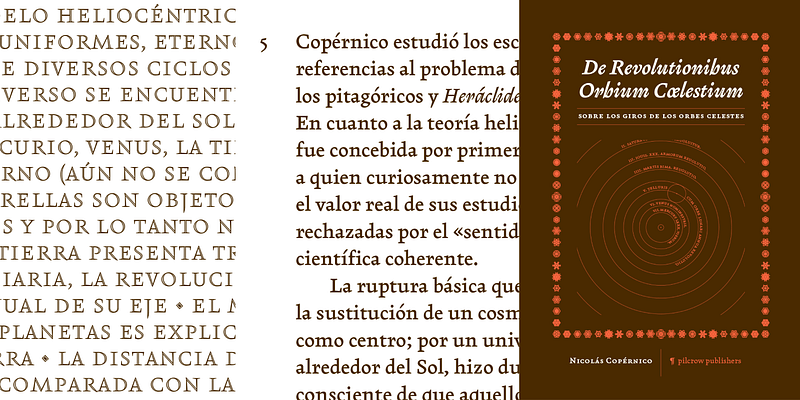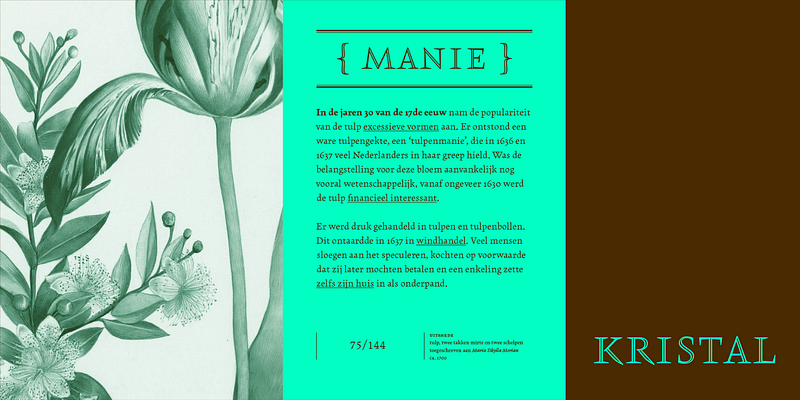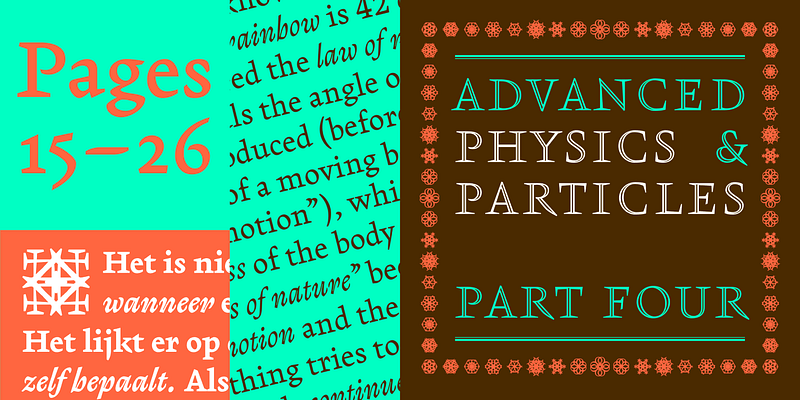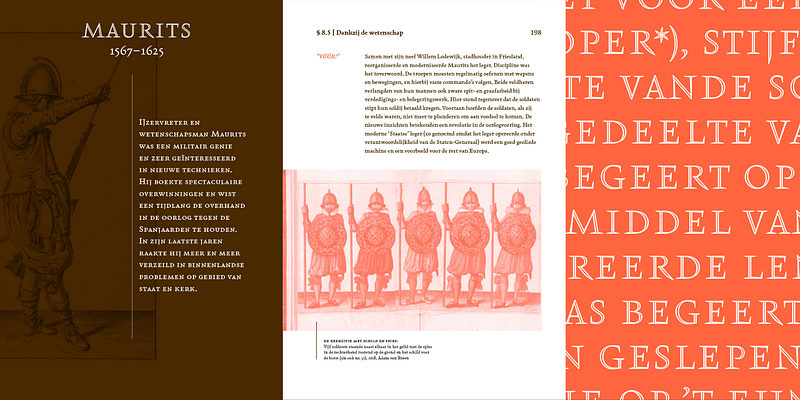
Il y a de cela plusieurs années, Kristal est née d’une esquisse pour un logotype, pour ensuite laisser place à des idées et à une énergie qui n’avaient pas leur place dans un projet à long terme tout juste terminé et avec une liberté de design limitée. Depuis, Eyal Holtzman a développé ce design en une famille unique de huit polices : trois graisses avec des italiques vifs et saisissants et un style de titrage en ligne tout en majuscules. Une police Ornaments complète le jeu de caractères étendu et la prise en charge linguistique des styles de texte. En tant que typographie polyvalente pour l’édition, Kristal offre une expérience de lecture agréable tout en donnant au texte un caractère et un éclat très particuliers. Les extrémités pointues des lettres majuscules et minuscules, qui font presque penser à une lame, agrémentent chaque paragraphe. Opiniâtre et expressive, cette typographie reste toujours ancrée dans la calligraphie et facile à combiner avec d’autres écritures et polices de caractères. Le style d’affichage Open Caps évoque un look intemporel et festif, applicable à des lettrages géants, des cartes élégantes ou des motifs de couverture. Les polices de caractères ajoutent de la nuance et se combinent harmonieusement avec le reste de la famille, ou peuvent être utilisées seules.